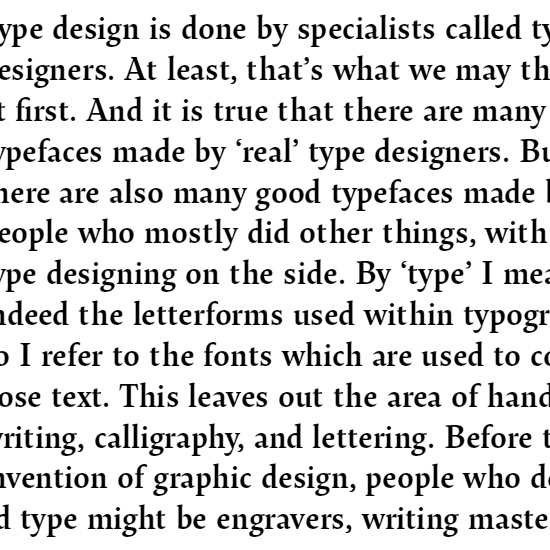
Lirico (OurType)
Hendrik Weber's Lirico is a characterful, contemporary text type that is at once elegant and sturdy, charming and reliable. It is the designer's first commercially available type, though it is by no means the work of a beginner. Weber is in fact an accomplished calligrapher and designer with a fine sensitivity to letterforms.
Weber began work on Lirico by creating the italic style first, then matching a roman to it. With the tradition and constraints of seriffed types in mind, Weber succeeds in bringing out a truly original design, without leaning on the work of other 'in-vogue' type designers, as so often happens these days. Specifically designed for texts, Lirico is unabashedly traditional yet pleasantly up-to-date. Its qualities will delight graphic designers and experienced typographers alike.
The Lirico family consists of roman and italic designs in six weights - ExtraLight, Light, Normal, SemiBold, Bold and Black - and one width. Next to the standard character set (STD), the pro character set (PRO) includes small caps; lining, old style and small cap figures (each in tabular and proportional widths); fractions; comprehensive superiors, inferiors, nominators and denominators; case sensitive punctuation sets; mathematical and monetary symbols; arrows; standard and discretionary ligatures; and a complete range of accents covering all (Latin script based) Western, Central and East European languages.
Die neu zu Ourtype dazugestoßenen Schriftgestalter haben übrigens auch Vornamen. Liricos Vater heißt Hendrik, Meran ist von Maurice Göldner und Alto von Thomas Tiemich, allesamt (Ex-) Studenten von Fred Smeijers.
Und allesamt haben sie sehr interessante Kursive. Merken.
Interessant das alle drei bei Fred Smejers an der HGB studiert
haben! Sehr Clever seinen Nachwuchs selber auszubilden.
Die Kombination, wie bereits erwähnt, „th“ stimmt nicht. Außerdem ist der Wortabstand im gezeigtem Muster für meinen Geschmack zu groß.
Im PDF sieht das »th« korrekt aus. Die Abbildung ist
ein Screenshot des vergrößerten PDFs und wahrscheinlich
irgendwie fehlerhaft.
Die brauch' ich nun nicht wirklich zu kennen? Nein. Denn wenn ich mich — wie eben geschehen — blaublind in die Lirico verliebe, heißt das doch nicht, dass ich gleich um ihre Hand anhalten will …
Sehr verehrte Damen und Herren, mein Name ist Hendrik Weber und ich freue mich über die Resonanzen zu „Lirico“ sehr.
Zu der Abstand-Problematik kann ich nur soviel sagen: der th-Abstand ist in dieser Abbildung zu groß aber definitiv ein Darstellungsfehler in der PDF.
Aber ich werde es noch mal überprüfen, wenn auch die Schriften nun auf dem Weg sind, nach zwei Jahren Entwicklung... bis bald Hendrik